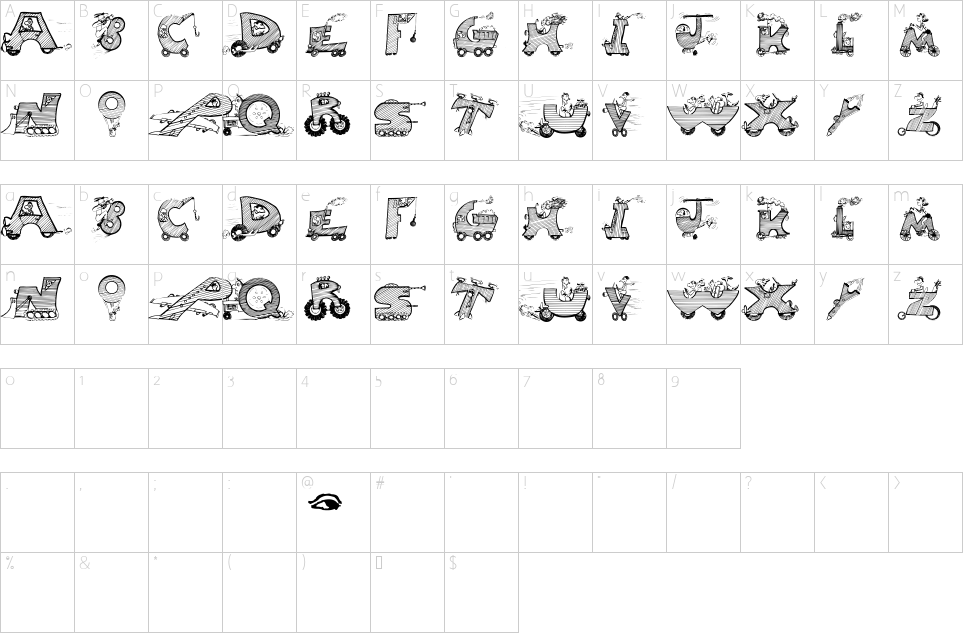
Descubra uma fonte única para seus projetos gráficos com Moving Letters, uma fonte grátis disponível para Windows e Mac. Designada por Manfred Klein, esta fonte traz um toque de movimento e originalidade a qualquer projeto. Ela foi descarregada 25,303 vezes, evidenciando seu potencial e relevância. Se você está procurando uma fonte que não apenas dá um tom único à sua criação, mas também proporciona um ar de movimento e alegria aos seus projetos, Moving Letters é uma excelente escolha. Sem dúvidas, ela é uma excelente adição para qualquer designer de gráficos, oferecendo alegria e criatividade sem limites.